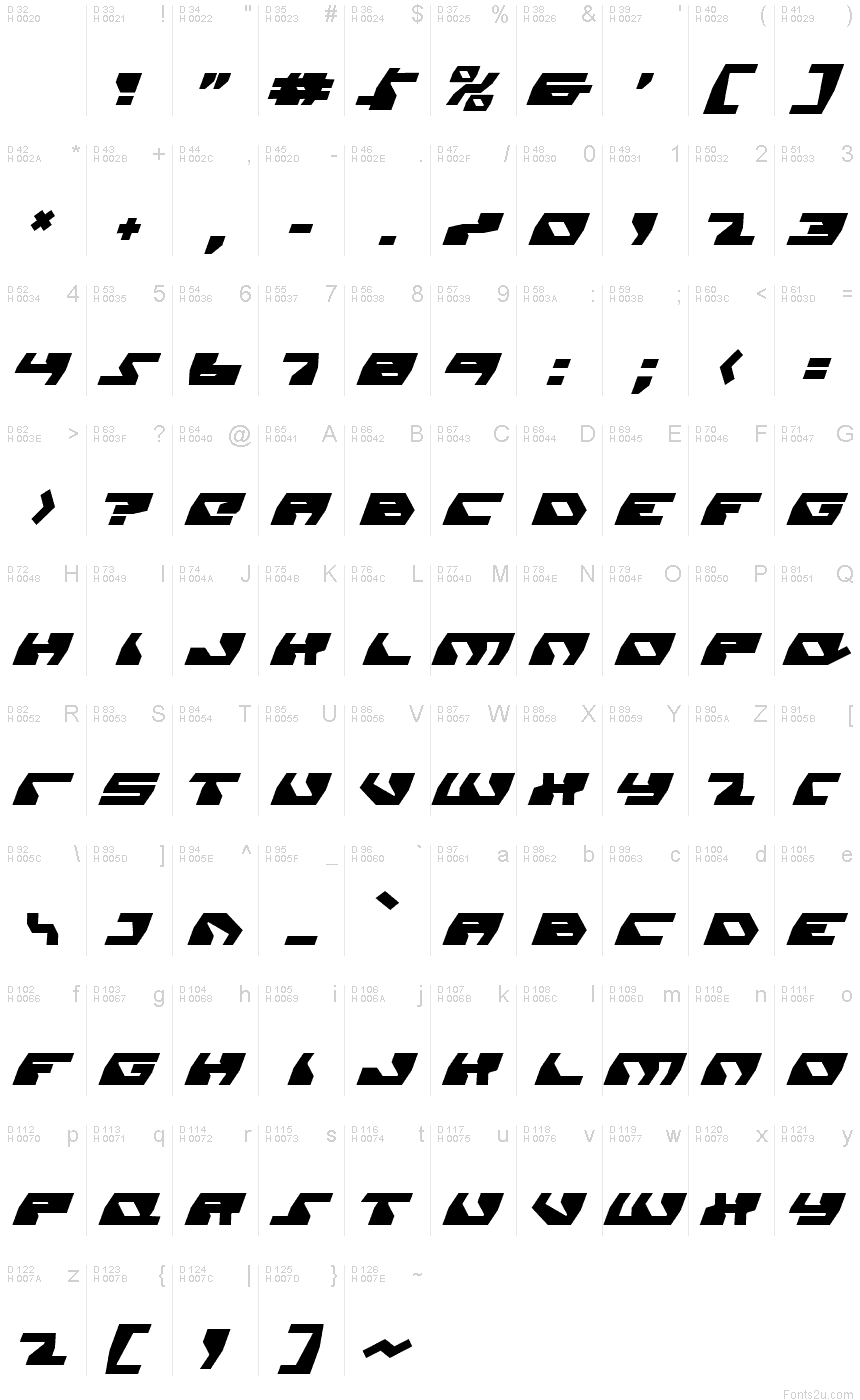
Daedalus Italic od Iconian Fonts to bezpłatny techniczny krój displayowy o ostrym, futurystycznym charakterze sci-fi. Litery zbudowane są z wyraźnych, ukośnych cięć i szerokich geometrycznych brył, co nadaje fontowi szybki, inżynieryjny rytm, bardziej kojarzący się z grafiką statków kosmicznych niż ze zwykłymi napisami.
Naturalnie sprawdza się w logo gier, na ulotkach muzyki elektronicznej, plakatach, miniaturach streamów czy w oprawie wizualnej wydarzeń technologicznych, gdzie dzięki swoim ściętym kształtom nadaje krótkim tekstom dynamicznego wyglądu. Jako bezpłatny font, świetnie sprawdzi się również w tytułach i monogramach, gdy potrzebujesz surowego, futurystycznego wyrazu bez miękkich krzywizn czy chromowanych efektów retro.
Daedalus Italic
Dan Zadorozny